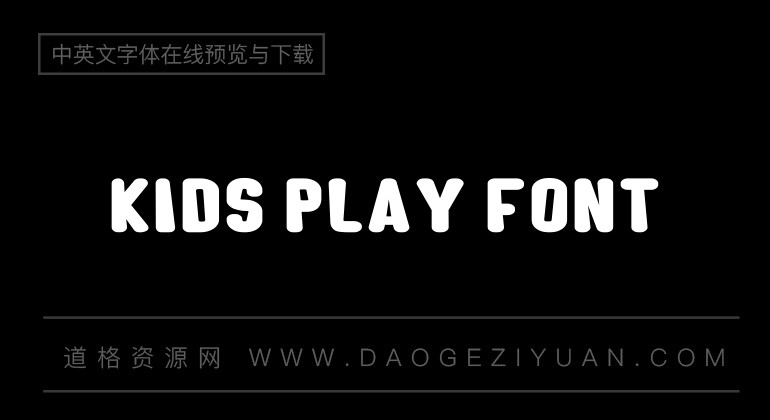
Kids Play Font 是一种可爱的手写字体,适用于儿童和儿童相关的设计项目。它有一种轻松、幼稚的感觉,完美地捕捉了儿童的想象力和创造力。这种字体被设计成类似于孩子们的手写,具有不规则的笔画和细微的偏移,以增加其独特的外观。 Kids Play Font 有两种版本,包括常规和粗体,以适应不同的设计需求。它可以用于海报、书籍、卡片、标志、广告等各种设计项目。在与其他图像和设计元素组合时,Kids Play Font 可以带来很好的视觉效果,并增强项目的可读性和吸引力。 总的来说,Kids Play Font 是一款非常适合儿童相关设计项目的可爱手写字体,具有独特的外观和视觉效果。内容介绍
Kids Play Font是一款非常不错的手写艺术字体,具有很好的视觉感,适合于文化类的宣传设计、商业类品牌的广告和产品包装设计以及个性化文字排版等较多场景。